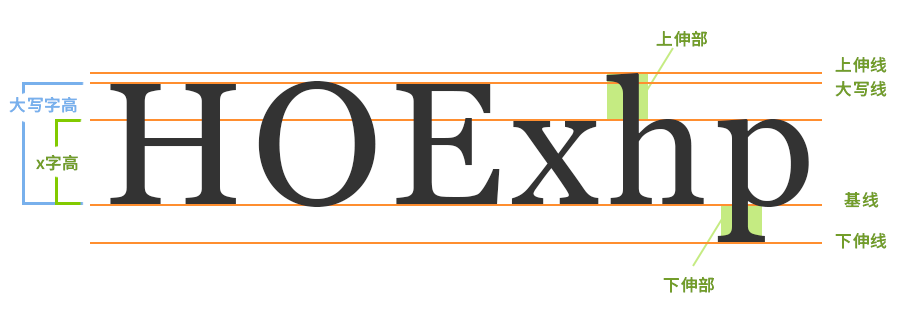
与中文的方块字不同,西文的基本单位是不等宽的字母,构成字母的笔画包含大量的曲线,并且西文需要将字母组合成单词来表达含义。
西文设计中的基础参考线也与汉字设计有所区别,想了解汉字设计中有哪些参考线可以阅读《字体设计指南:解密字面框》。那下面就来了解一下西文设计中有哪些专业术语吧!
大写线(cap line):与大写字母顶端平齐的这条参考线被称为大写线,大写线与基线之间的高度差叫做大写字高(cap height)。
基线(base line):与大写字母底端平齐的参考线,是西文字型拥有共同的基线。
上伸线(ascender line):小写字母高于x字高的部分,其对齐的线被称为“上伸线”,这部分的高度被称为上伸部高(ascender height)。
下伸线(descender line):小写字母低于基线的部分,叫作下伸部(descender)。而下伸部对齐的线,就叫做“下伸线”。